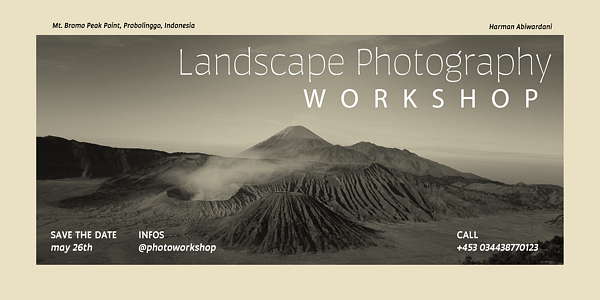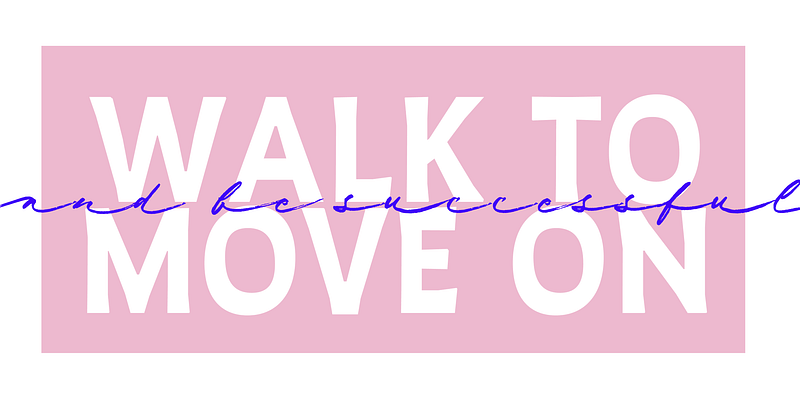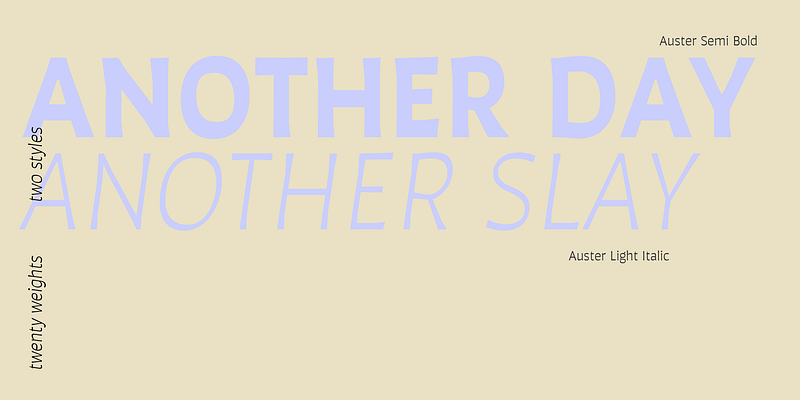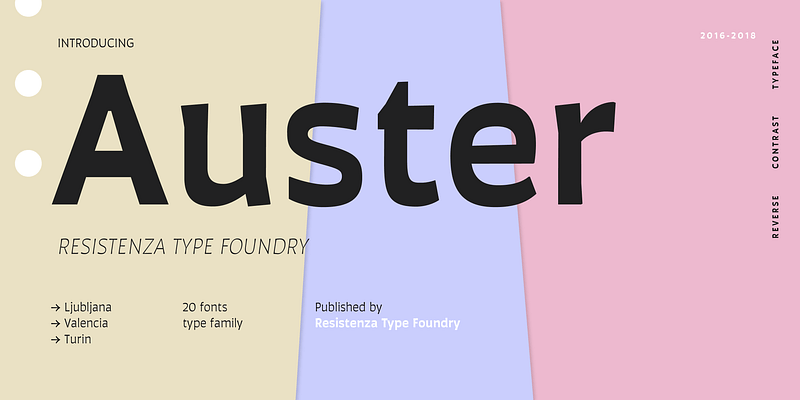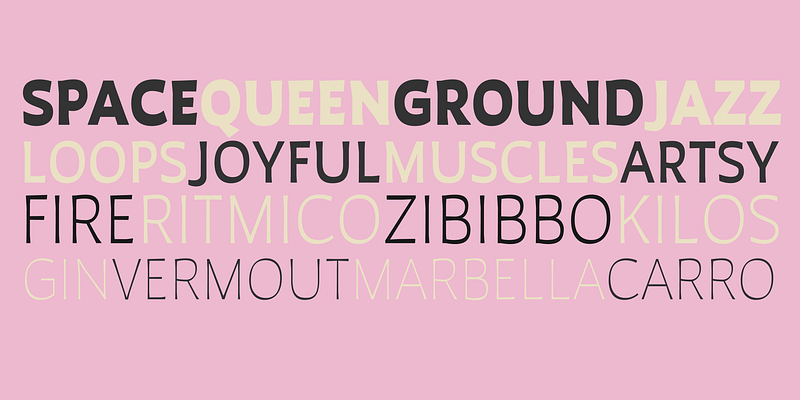
Resistenza es una empresa de tipografía formada por Giuseppe Salerno, un calígrafo titulado con experiencia en diseño gráfico adquirida en Torino, Italia, y Paco González, un diseñador autodidacta español procedente de Valencia. Su trabajo es principalmente manual y así logran dotar de un carácter rompedor y humanista a sus estilo de diseño gráfico, haciendo hincapié en la creación de lazos con lugares y personas que usan un producto o servicio en particular. A menudo, Resistenza crea colecciones de sus tipos de letra para trabajar con series o familias tipográficas, partiendo de una marca que pueda funcionar en todo el diseño. Su capacidad para crear bibliotecas de fuentes Brush Script y tipografías caligráficas, así como ilustraciones únicas, bocetos, iconos, etc., les permite complementarse cuando colaboran para un cliente en particular. Lo que verdaderamente buscan es hacer que las fuentes cobren vida y para ello empiezan con el método tradicional de la pluma y el papel para más tarde implementar el proceso de digitalización. A partir de ahí, estos dos especialistas ponen de manifiesto los rasgos diferenciadores de sus estilos de letra gracias a las influencias que reciben de las distintas ciudades en las que trabajan y viven: Berlín, Madrid, Torino y Valencia.